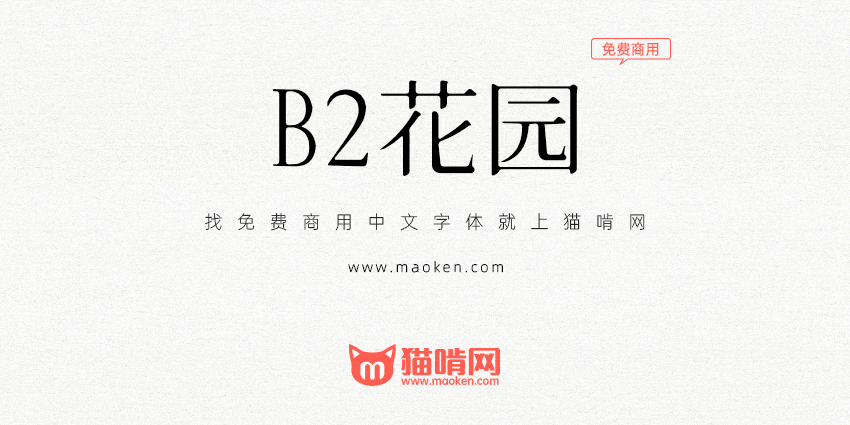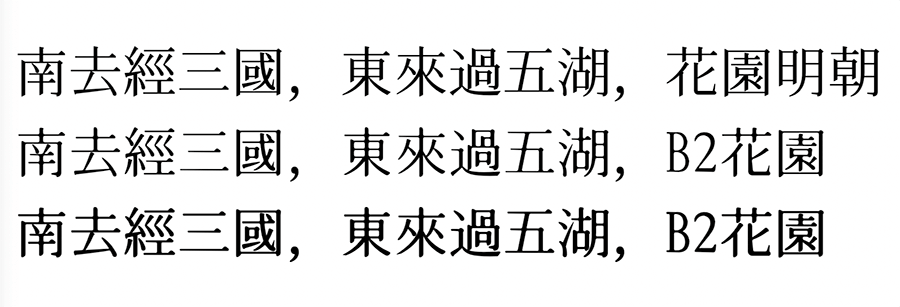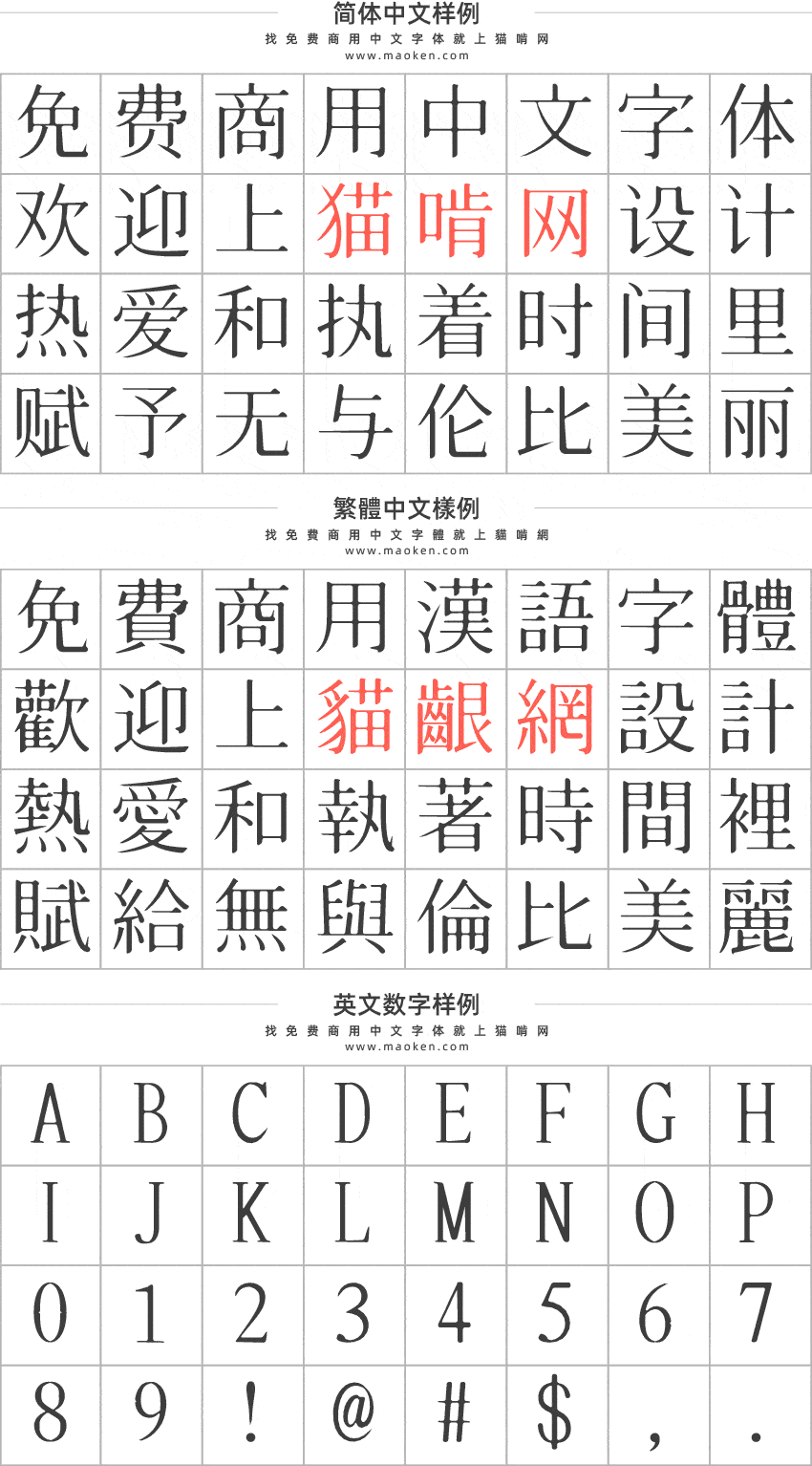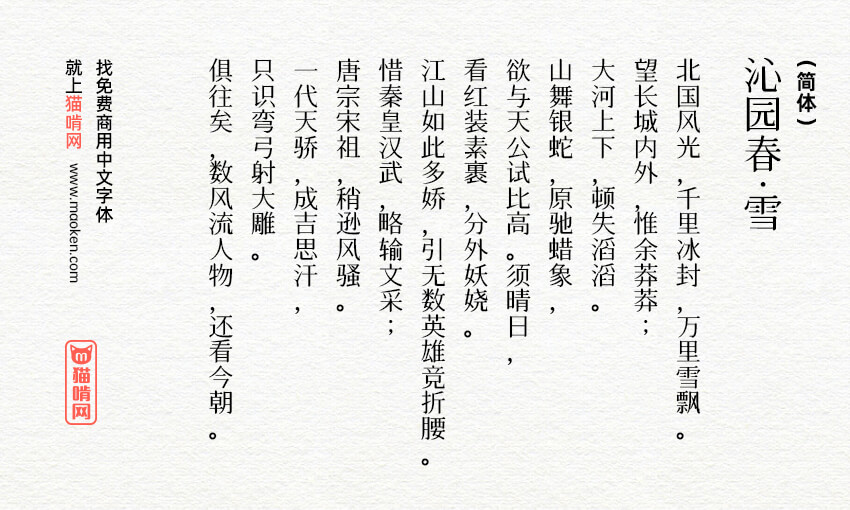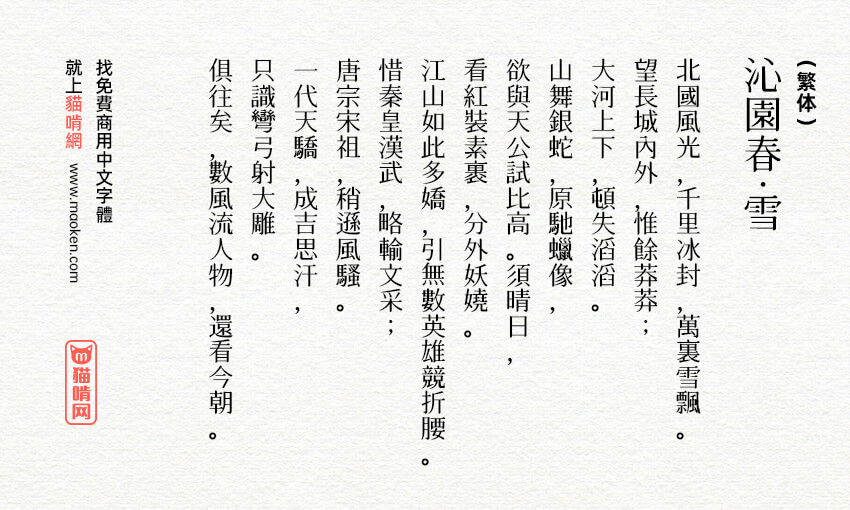
B2花园使用“狮尾B2宋朝”字体的处理程序,套用到“花园明朝”字体后,效果满好的,分享较圆的“花园明朝”字体给大家使用。
B2花园字体是基于花园明朝的转角的三角形转成半圆形改造,彷彿墨晕或是稍微过曝的效果。欢迎大家自由使用、自由优化、自由改作!
本字体是改造自グリフウィキ(GlyphWiki)所开发、发表的“花园明朝(花园フォントについて)”字型。